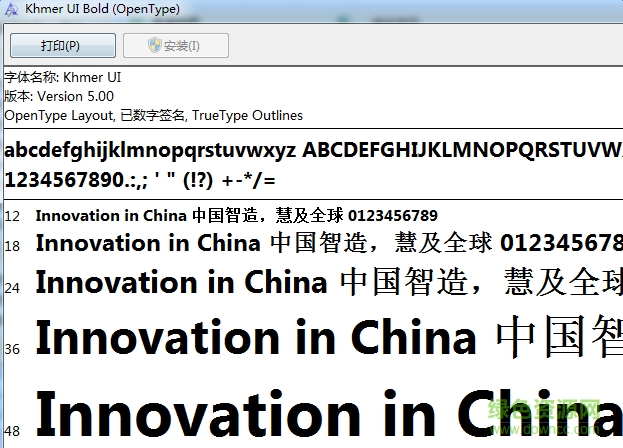
khmerui bold字體
khmerUI字體是一款超好用的個性英文字體,該字體可以廣泛應用于廣告設計、宣傳海報、ppt、影視制作以及任何使用文字的領域,有需要的朋友可以免費下載收藏。
khmerUI字體是一款極具個性的字體,該字體十分飄逸,彰顯了自己的個性,有喜歡的朋友可以來綠色資源網(wǎng)下載使用!